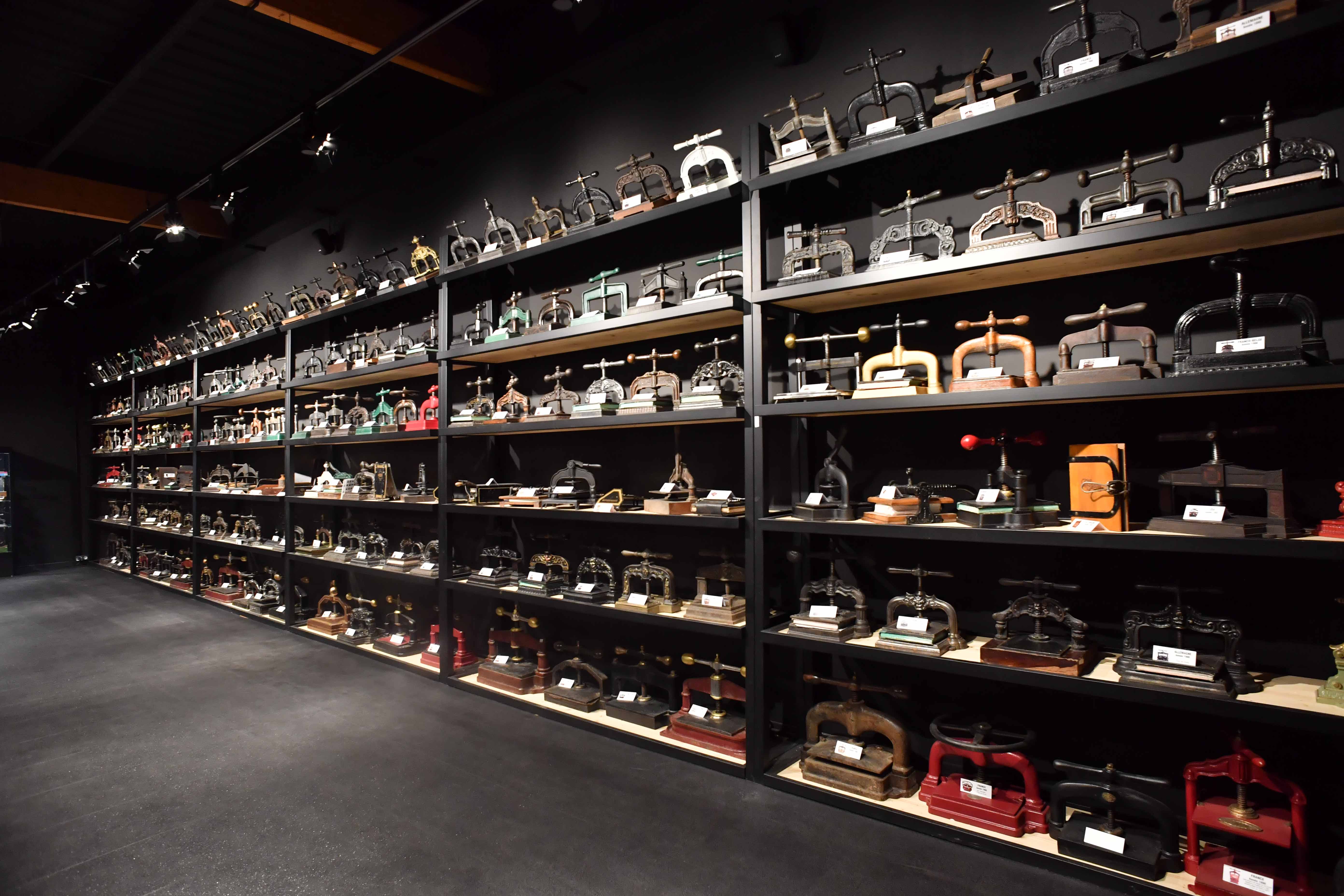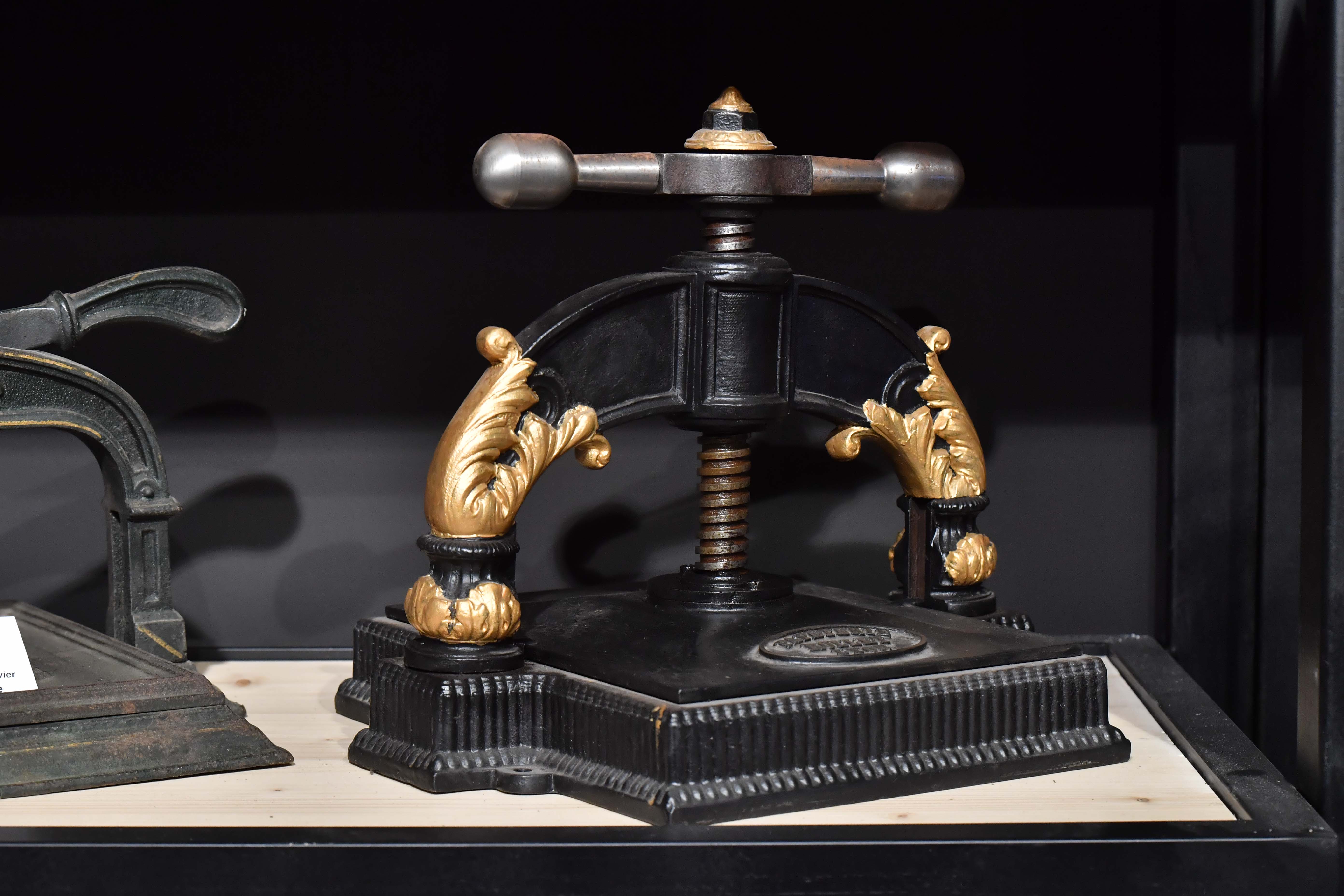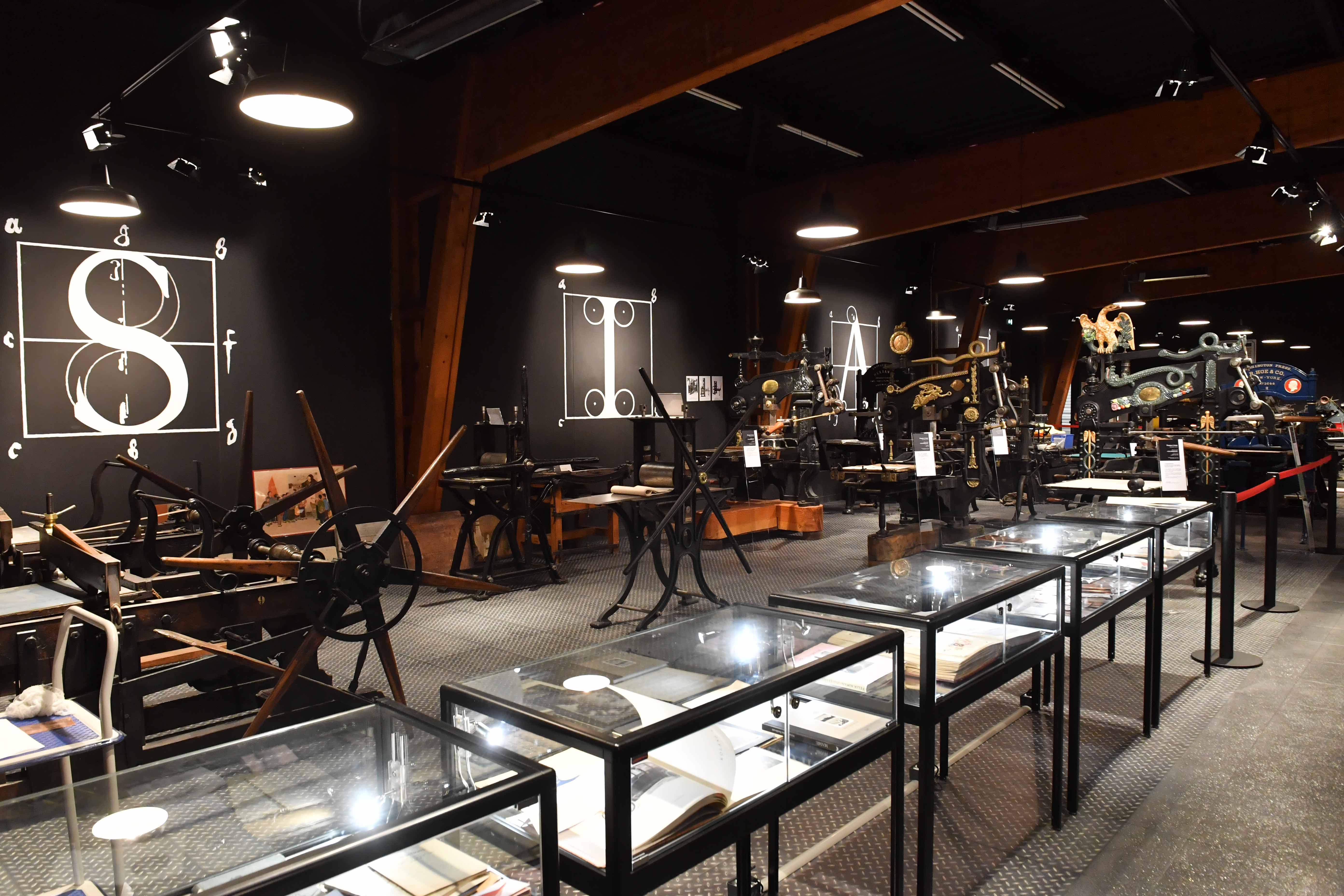
Toute une Histoire !
« L’invention de l’imprimerie est le plus grand événement de l’Histoire. C’est la révolution-mère. C’est le mode d’expression de l’humanité qui se renouvelle totalement. » Victor Hugo
Plongez dans cet univers, la belle odyssée technique et culturelle de l’imprimerie : de l’invention du papier jusqu’au premier livre – la bible à 42 lignes – imprimé par Gutenberg au XVème siècle en passant par l’incroyable saga des moines copistes du Moyen-Âge, revivez en textes et en images ce que furent les premiers pas de l’art typographique : le codex manuscrit, ancêtre du livre moderne, puis l’invention de la typographie par Gutenberg , prélude à la diffusion de l’imprimerie dans toute l’Europe.
Dans l’atelier de Gutenberg
Un petit atelier d’où l’on perçoit, par delà la lucarne, les bruits du dehors, le brouhaha de la rue dans le parfum entêtant de l’encre d’imprimerie… Nous sommes au XVème siècle, les apprentis et les compagnons travaillent à la réalisation des premières impressions de l’histoire de la typographie.
L’atelier du temps de Gutenberg a été reconstitué. Celui qu’on considère comme le père de l’imprimerie fut le premier à mettre au point la technique des caractères mobiles reconductibles et réutilisables à l’infini, selon un alliage de plomb, d’étain et d’antimoine.
Le premier livre répertorié de la sorte fut la bible à quarante deux lignes de 1286 pages et tirée à 180 exemplaires.
Le parcours d’une vie
La salle d’accueil du musée retrace autour du « marbre » ce que furent les grands moments de la carrière professionnelle de Fernand Le Rachinel imprimeur normand, propriétaire des lieux et Meilleur Ouvrier de France : de ses débuts comme jeune apprenti chez Jacqueline, l’imprimeur Saint-Lois, jusqu’à la mise en œuvre de la SIAL- la Société d’Impression d’Art Le Rachinel – dont les anciens locaux installés dans les années 80 sur la zone d’activités de la Chevalerie abritent aujourd’hui ce musée exceptionnel.
Cinema : l’imprimerie crève l’écran
Le musée propose dans sa salle de cinéma la diffusion de nombreux films et documents d’archives consacrés à l’histoire de l’imprimerie. On voit revivre l’époque de Gutenberg et l’ensemble des techniques d’impression y sont détaillées, des premiers caractères linotypes jusqu’à l’ère du numérique, une formidable saga racontée en images.
Les salles des machines
Le clou de la visite, la salle des machines ! L’espace regroupe de très nombreux modèles uniques et authentiques, tous en état de marche, une incroyable et magnifique collection.
Chaque modèle présenté est une histoire. Cette salle d’exposition nous présente de nombreuses pièces uniques et rares, presses à bois « bêtes à corne », caractères de plomb et de bois, les pierres lithographiques, les plaques de cuivre, les machines dites à taille douce… etc.
Autour du marbre et des tables de montage, à l’ombre des casses d’antan, l’espace reconstitue un atelier aux mille facettes et aux multiples collections conservées en l’état dont entre autres cette machine qui servit à l’impression des menus de l’Elysée et dont les bras conservent encore, bien des années après, la marque de l’encre séchée, témoignage émouvant du labeur des hommes, les compagnons typographes dont le travail complexe et rigoureux allait changer le monde !
A découvrir dans le prolongement de la salle des machines l’espace consacré aux photocopieuses d’autrefois. Le musée en présente plus de 200, ce sont les presses dite de notaires, les ancêtres de nos actuels photocopieurs et dont l’invention remonte à 1780. Une collection unique en France !